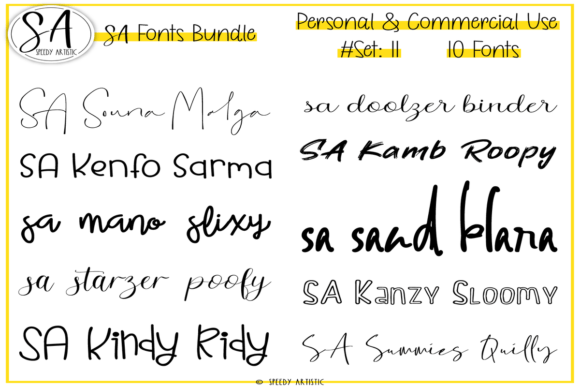
Script and Handwritten Bundle 11
Script and Handwritten Bundle 11와 같은 κ³ ν’ˆμ§ˆ μžμ‚°μ„ μ°Ύκ³  μžˆλ‹€λ©΄ 이 프리미엄 νŒ¨ν‚€μ§€λŠ” 창의적인 ν”„λ‘œμ νŠΈλ₯Ό μœ„ν•œ ν™˜μƒμ μΈ μ„ νƒμž…λ‹ˆλ‹€.
μ •λ°€ν•˜κ²Œ μ œμž‘λœ Script and Handwritten Bundle 11λŠ” κΉ”λ”ν•œ 벑터, λΆ€λ“œλŸ¬μš΄ νƒ€μ΄ν¬κ·Έλž˜ν”Ό 및 μ•ˆμ‹¬ν•  수 μžˆλŠ” μƒμ—…μš© λΌμ΄μ„ μŠ€λ₯Ό μ œκ³΅ν•©λ‹ˆλ‹€.
POD(μ£Όλ¬Έν˜• 인쇄) μ œν’ˆ, κ²°ν˜Όμ‹ μ΄ˆλŒ€μž₯ λ˜λŠ” μ†Œμ…œ λ―Έλ””μ–΄ κ·Έλž˜ν”½μ„ λ§Œλ“€ λ•Œ Script and Handwritten Bundle 11λŠ” 이상적인 μ„ νƒμž…λ‹ˆλ‹€.